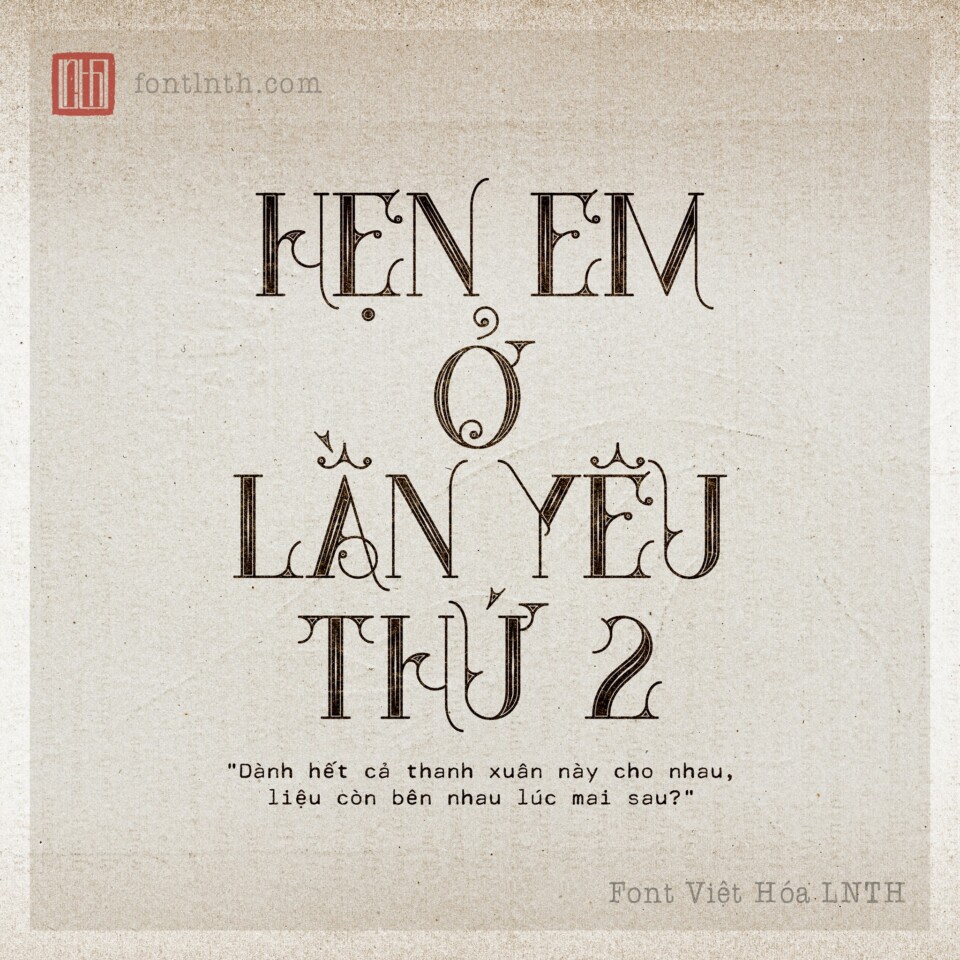
Font Việt hóa LNTH StarBlackInline
Giới thiệu về Font Việt hóa LNTH StarBlackInline
Trong thế giới đồ họa hiện đại, việc tìm kiếm một bộ Font Miễn Phí chất lượng luôn là ưu tiên hàng đầu của các bạn trẻ. Font Việt hóa LNTH StarBlackInline là một cái tên nổi bật trong bộ sưu tập phông chữ nghệ thuật. Đây là phiên bản được tinh chỉnh kỹ lưỡng, hỗ trợ đầy đủ các ký tự tiếng Việt, giúp người dùng dễ dàng ứng dụng vào các dự án sáng tạo mà không lo lỗi hiển thị. Với phong cách mạnh mẽ và đường nét cá tính, bộ phông này mang lại sự chuyên nghiệp cho mọi bản thiết kế.
Đặc điểm nổi bật của bộ font chữ
Đúng như tên gọi, Font Việt hóa LNTH StarBlackInline sở hữu phong cách “Inline” đặc trưng với một đường kẻ rỗng ở giữa thân chữ. Thiết kế này tạo nên hiệu ứng thị giác 3D độc đáo, giúp các tiêu đề trở nên nổi bật và thu hút ánh nhìn ngay lập tức. Phông chữ này đặc biệt phù hợp cho các bạn học sinh dùng để trang trí báo tường, làm bìa tiểu luận hoặc thiết kế slide thuyết trình trên lớp. Sự kết hợp giữa nét dày đậm và khoảng hở tinh tế mang lại cảm giác vừa cổ điển vừa hiện đại cho tác phẩm.
Cách ứng dụng Font Việt hóa LNTH StarBlackInline hiệu quả
Để tận dụng tối đa vẻ đẹp của Font Việt hóa LNTH StarBlackInline, bạn nên sử dụng chúng cho các tiêu đề chính hoặc các đoạn văn ngắn cần sự nhấn mạnh. Bạn có thể kết hợp phông chữ này với các tông màu tương phản như vàng đen hoặc trắng xanh để làm nổi bật hiệu ứng đường kẻ. Ngoài ra, phông chữ còn rất thích hợp cho việc thiết kế logo đội nhóm hoặc in ấn áo đồng phục lớp, giúp thể hiện phong cách riêng biệt và năng động của lứa tuổi học trò.
Dù là một phông chữ đẹp, bạn không nên dùng Font Việt hóa LNTH StarBlackInline cho các đoạn văn bản dài vì cấu trúc phức tạp của nó có thể gây mỏi mắt. Hãy giữ nó như một điểm nhấn nghệ thuật trong bố cục tổng thể của bạn.